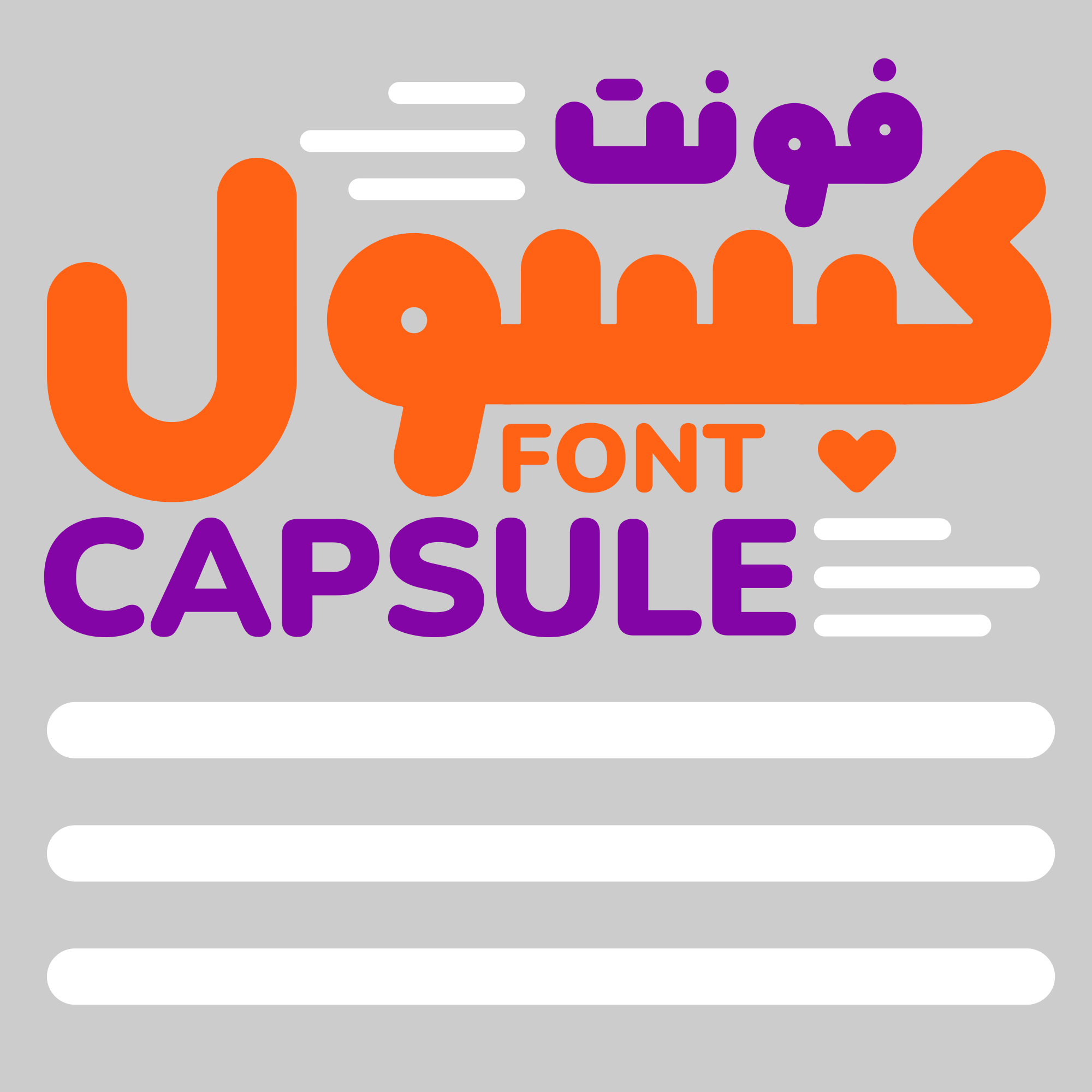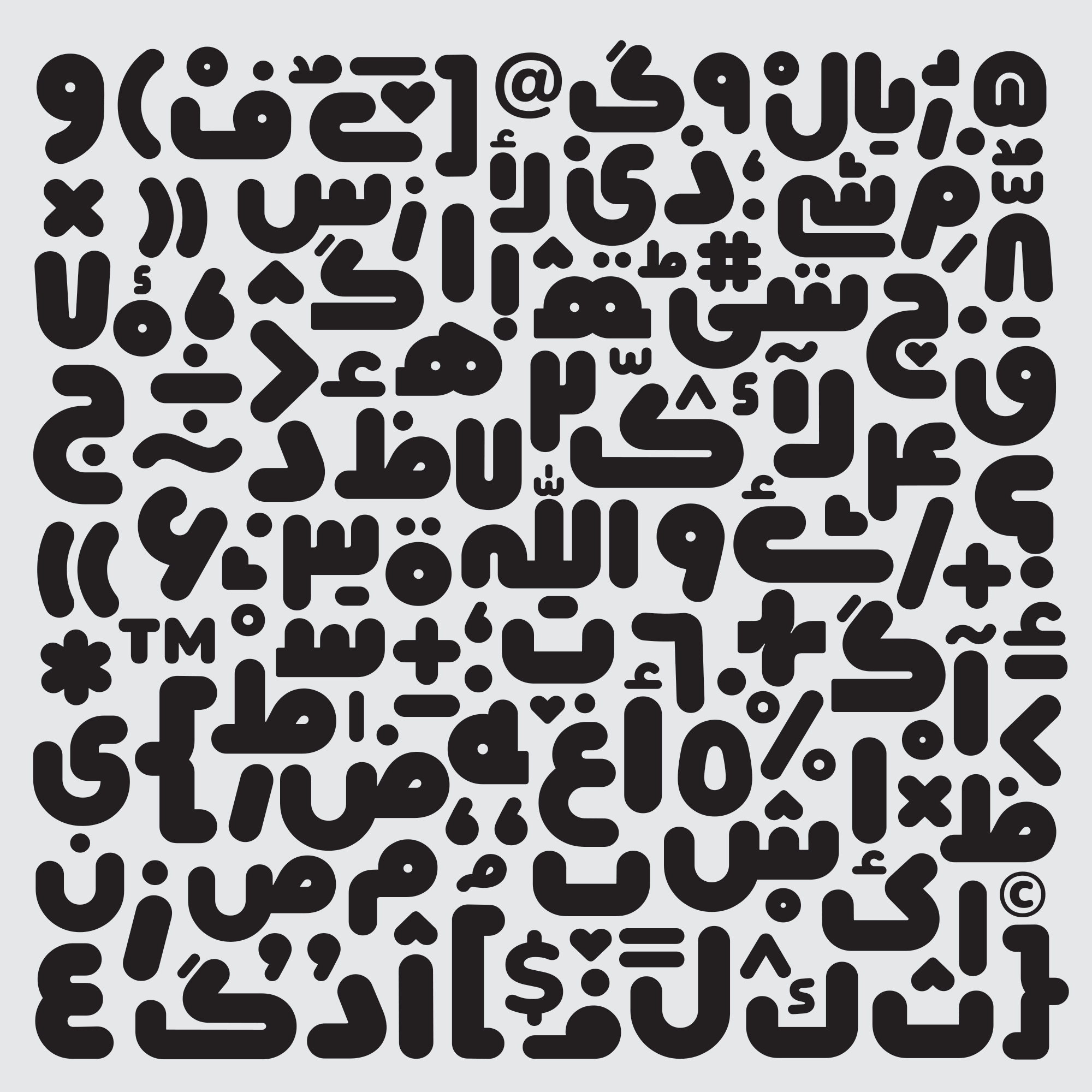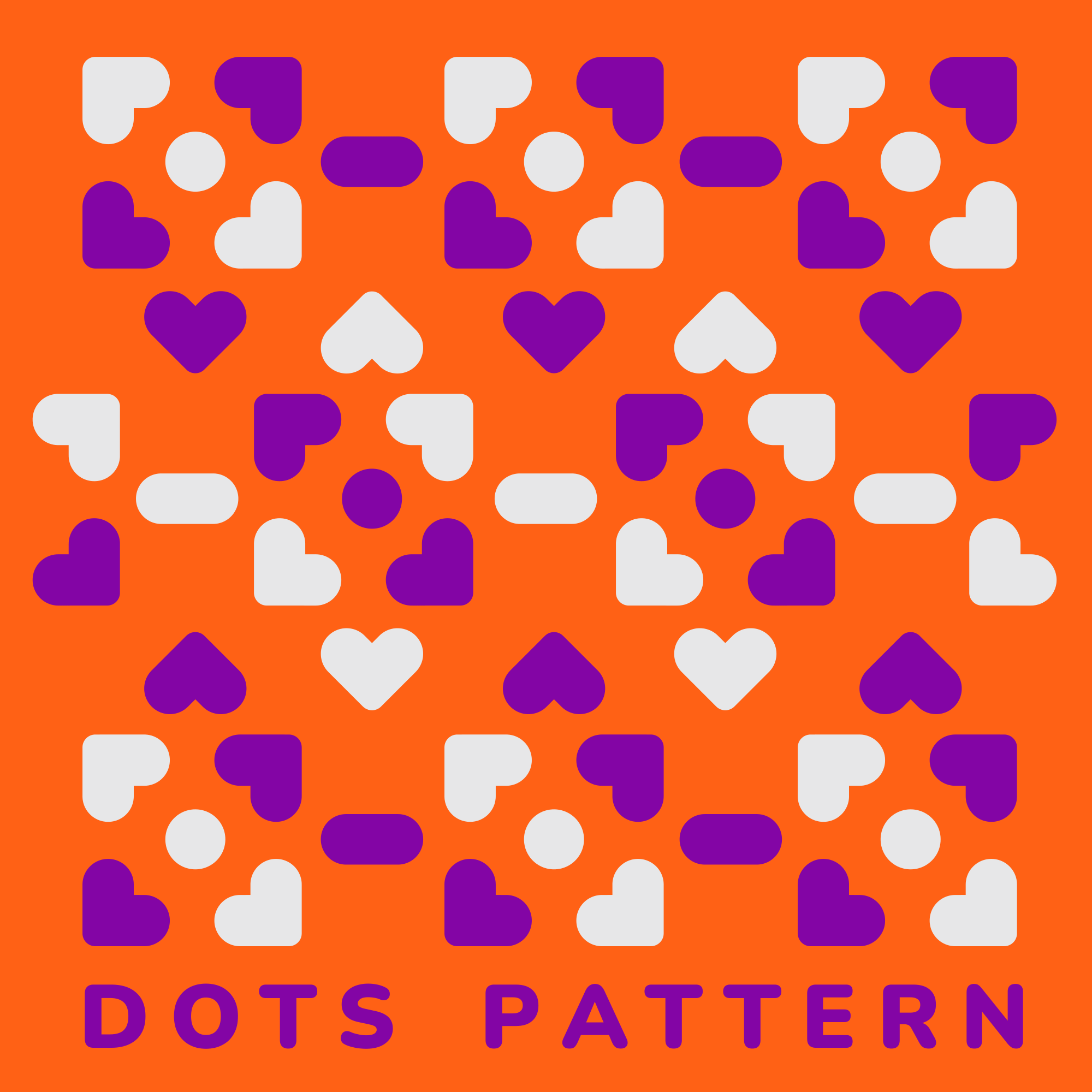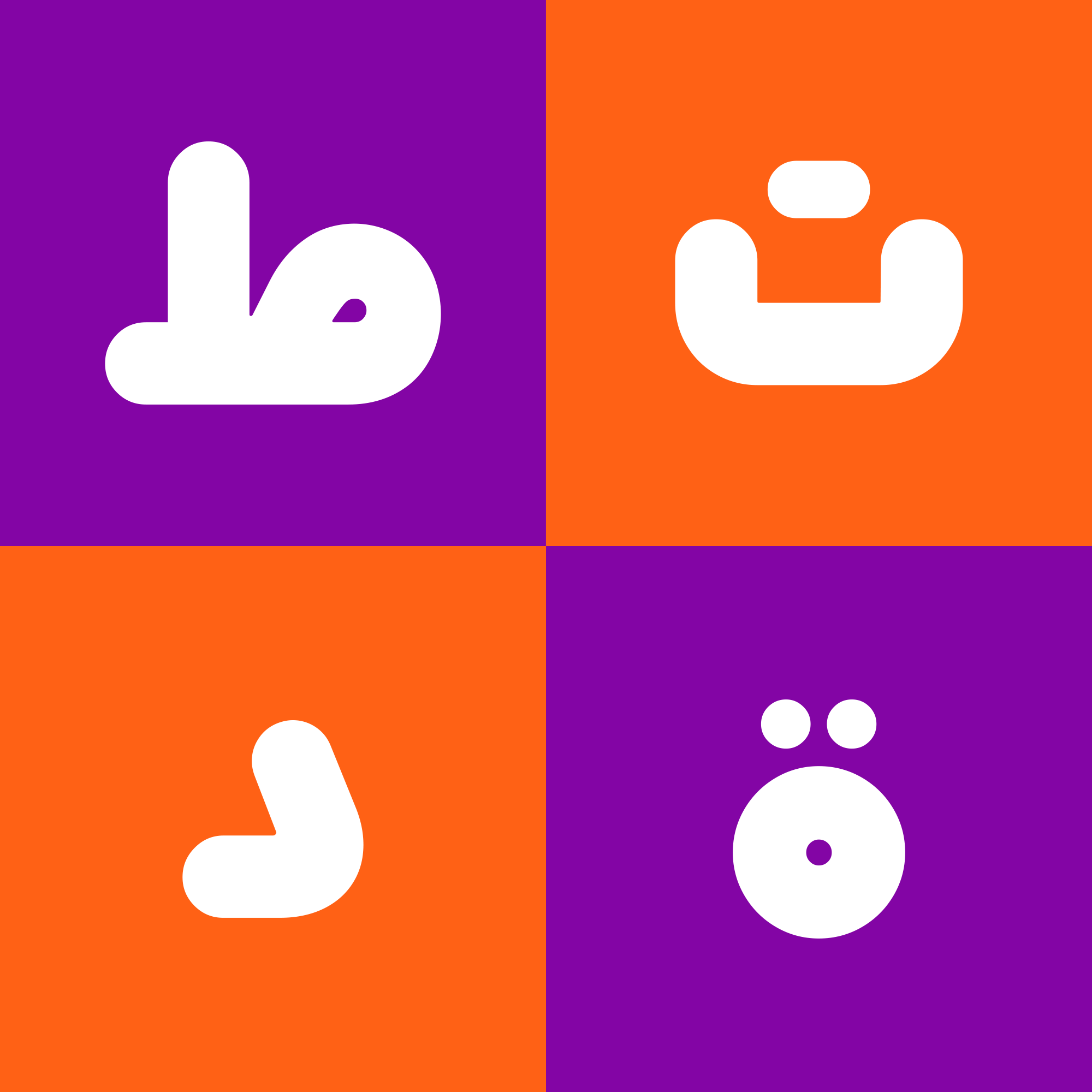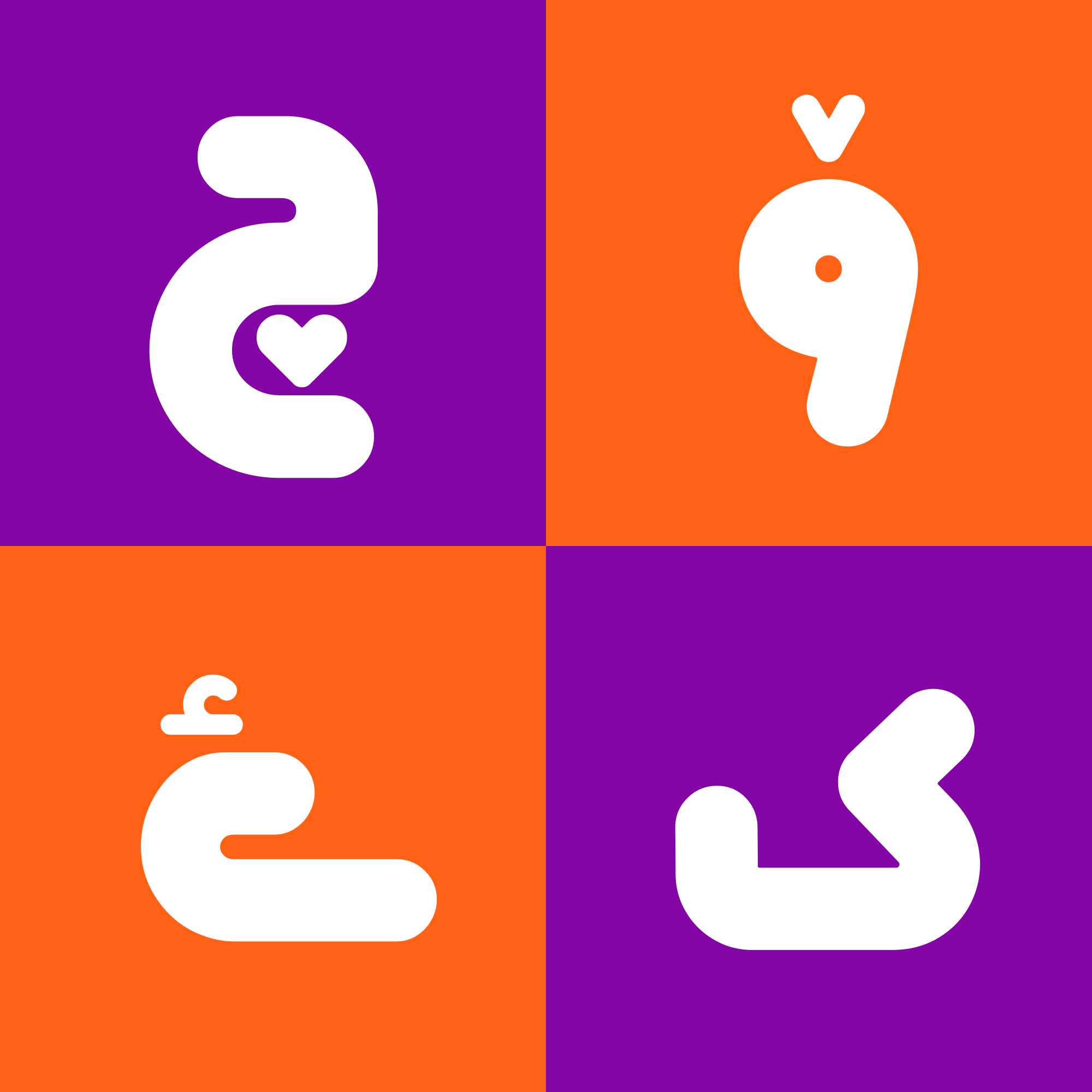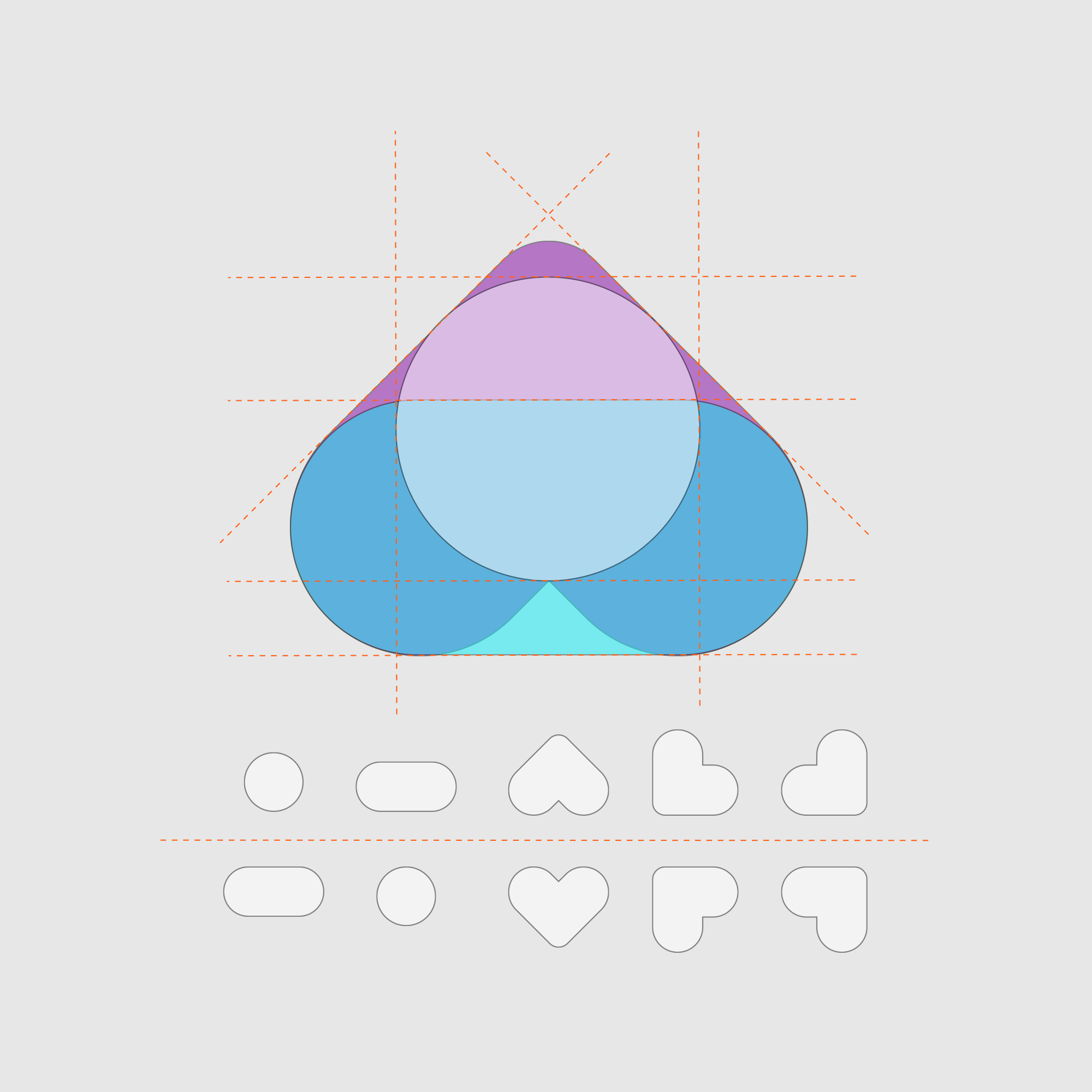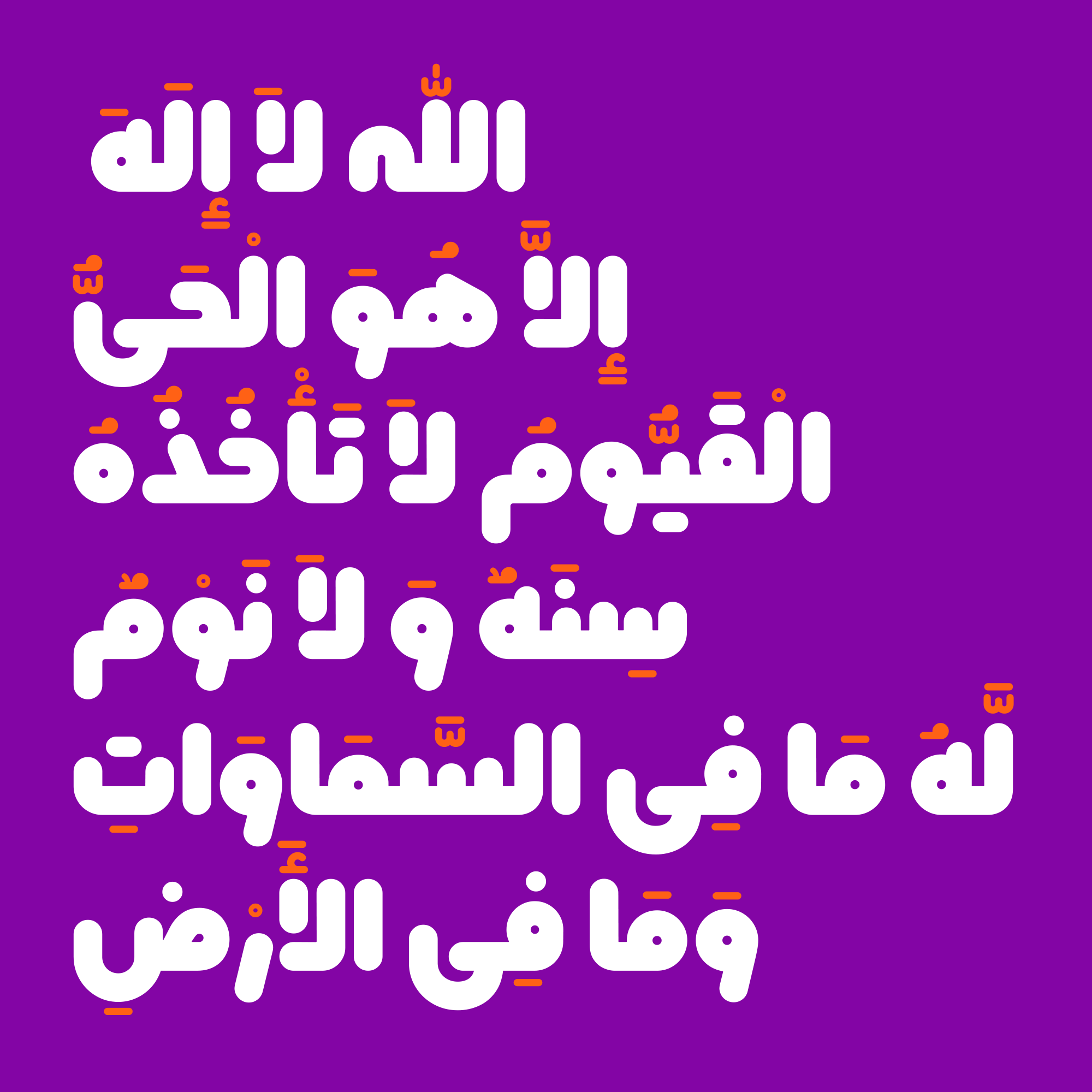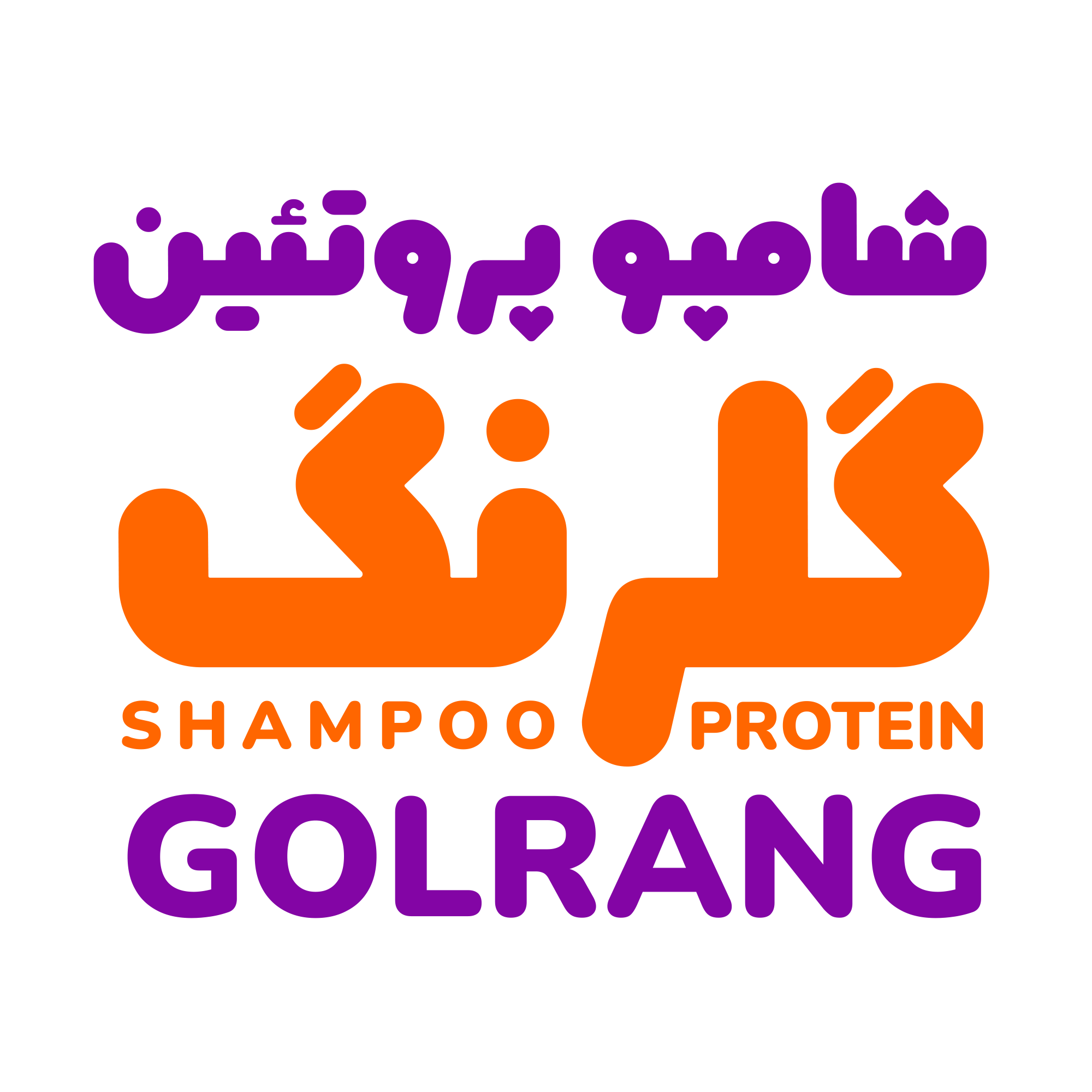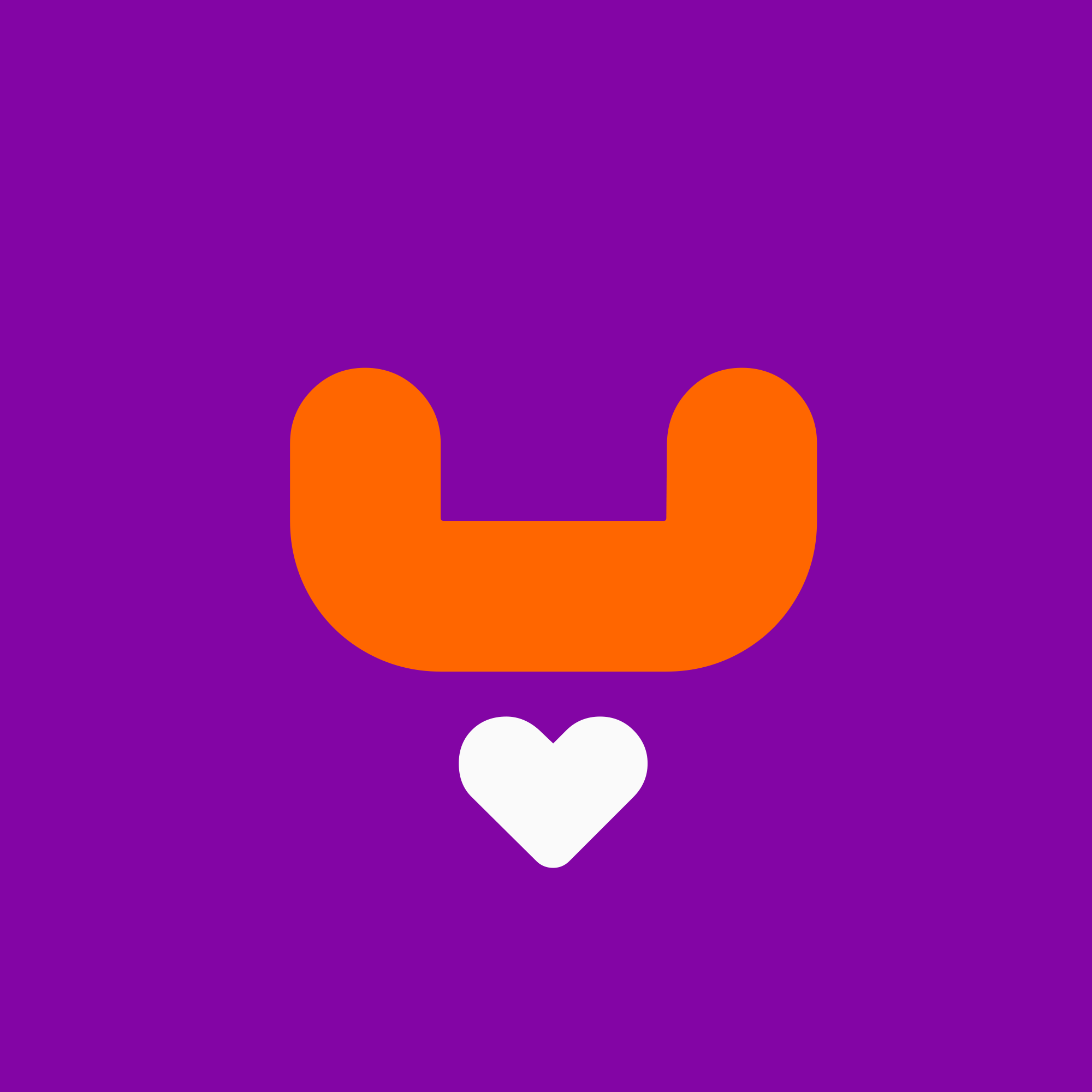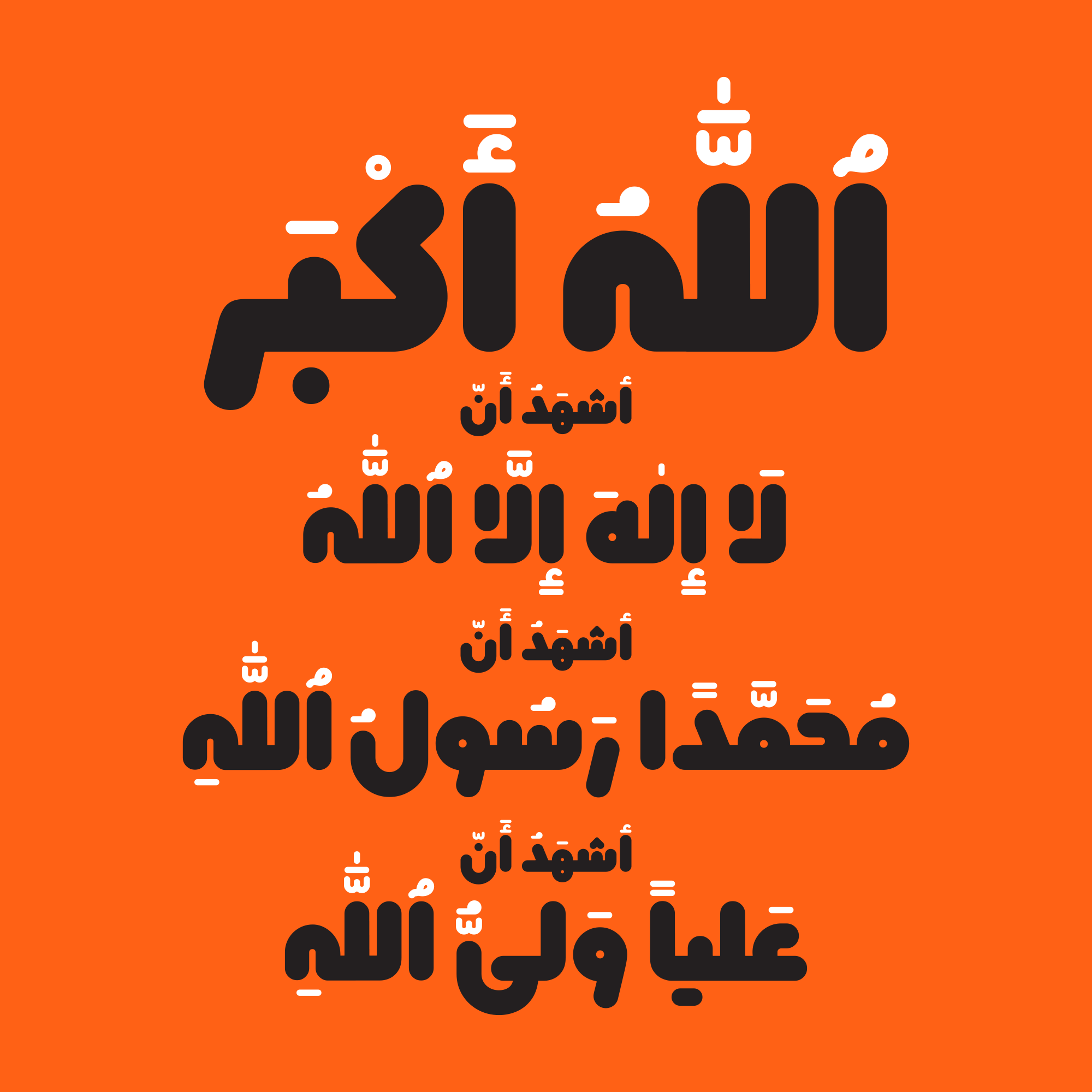
این فونت از زبان فارسی، عربی و انگلیسی پشتیبانی میکند.
در فونت کپسول حروف جایگزین شامل: کـ ـکـ ـک ک ، گـ ـگـ ـگ گ، پـ ،بـ ، نـ ، یـ ، ئـ ، تـ ، و، ر، ژ،ز، ـهـ ، ـه، م، سـ، شـ می باشند. دراین فونت حروف 3 نقطه، داری حالت های مختلف هستند مثل ژ، چ، ث، ش،پ که با استفاده از کلیدهای میانبر و استایل ستها قابل تغییر می باشند.
فونت کپسول به لحاظ شخصیت و فرمی که دارد فقط برای نوشتن عبارات، کلمات و ترکیبهای مختصر کاربرد دارد و برای استفاده در متن و جملات طولانی توصیه نمیشود.